อย่างที่เราทราบกันดีว่าตัวอักษรภาษาอังกฤษจะมี 26 ตัวอักษร และยังแยกเป็นตัวพิมพ์เล็ก พิมพ์ใหญ่ด้วยเราเขียนตัวอักษรพวกนี้มาตั้งเด็กๆ จนโตแล้วคุณรู้สึกเบื่อบ้างไหม ถ้าวันนี้ตัวอักษรภาษาอังกฤษเหล่านี้ถูกออกแบบใหม่ เพื่อเอาใจเด็กๆ มากขึ้นจะเป็นอย่างไร
Simon Koay ศิลปินชาวออสเตรเลีย ได้รังสรรค์งานศิลปะของเขาผ่านตัวอักษรภาษาอังกฤษทั้ง 26 ตัวให้ดูทันสมัยมากขึ้น โดยใช้เป็นสัญลักษณ์ของฮีโร่ และเหล่าตัวร้ายที่ออกแบบใหม่อย่างคลาสสิก เรามาดูกันว่าเวอร์ชั่นไหนมันจะเจ๋งกว่ากัน
1. ตัวอักษร A ในสัญลักษณ์เป็น กัปตันอเมริกา
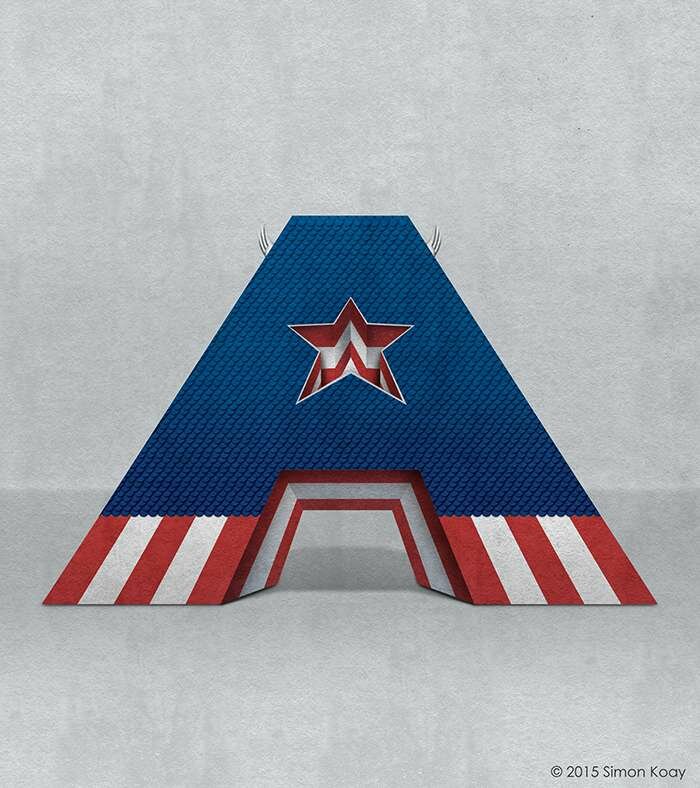
2. ตัวอักษร B ในสัญลักษณ์เป็น แบทแมน
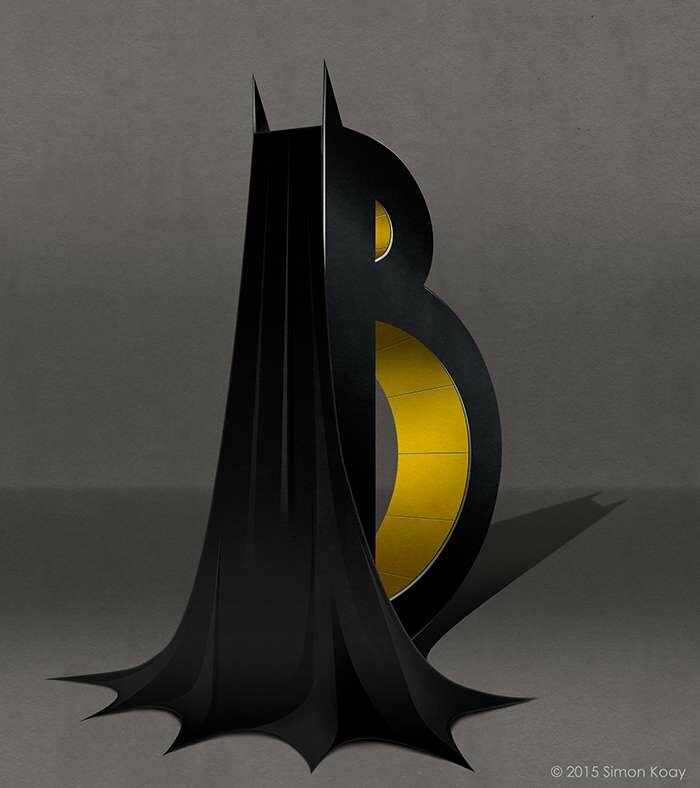
3. ตัวอักษร C ในสัญลักษณ์เป็น ไซคลอป
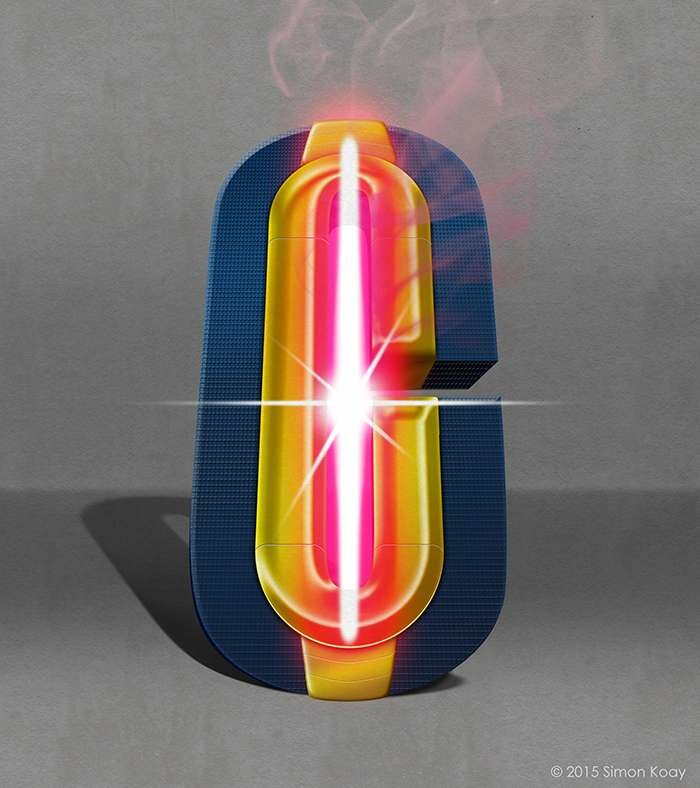
4. ตัวอักษร D ในสัญลักษณ์เป็น เดดพูล
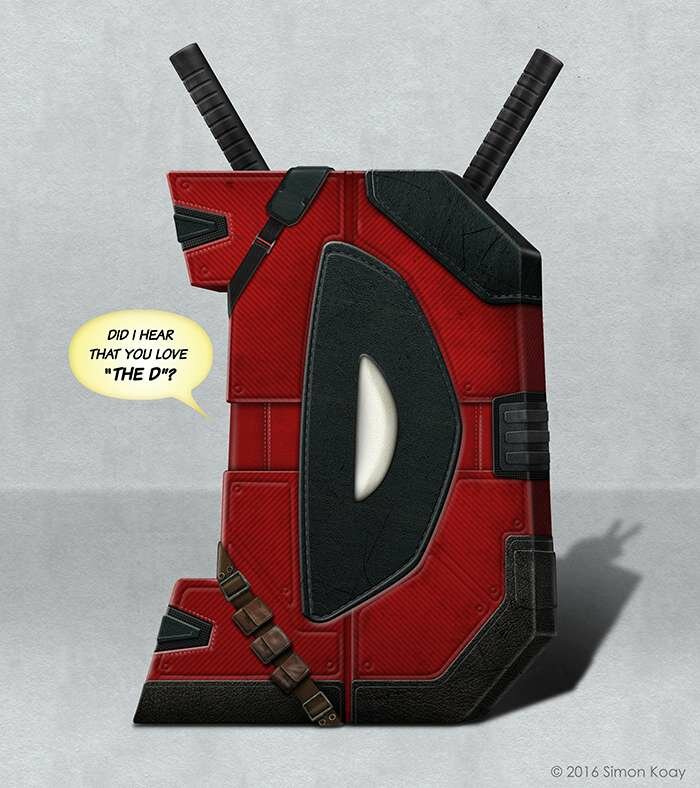
5. ตัวอักษร E ในสัญลักษณ์เป็น Elektra Black Angel
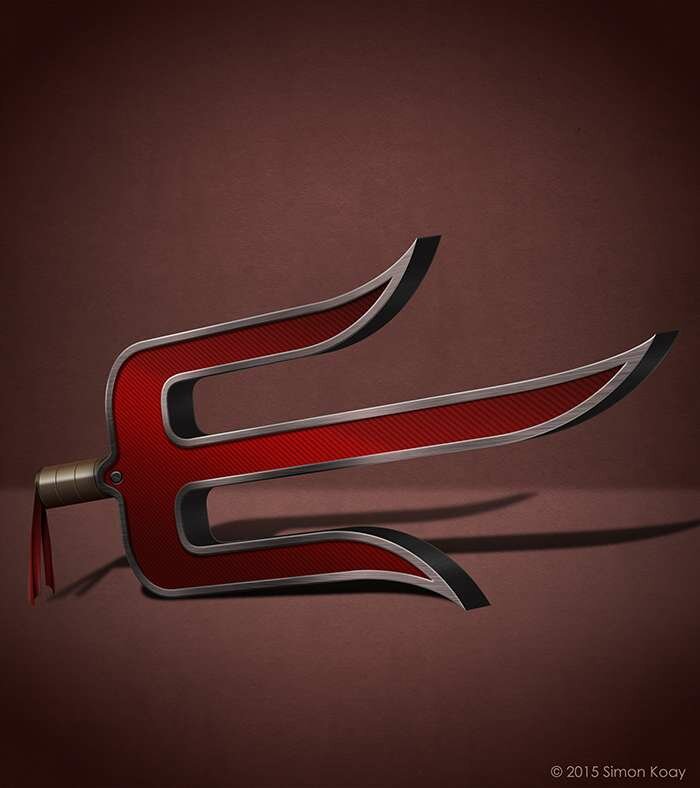
6. ตัวอักษร F ในสัญลักษณ์เป็น เดอะ แฟลช
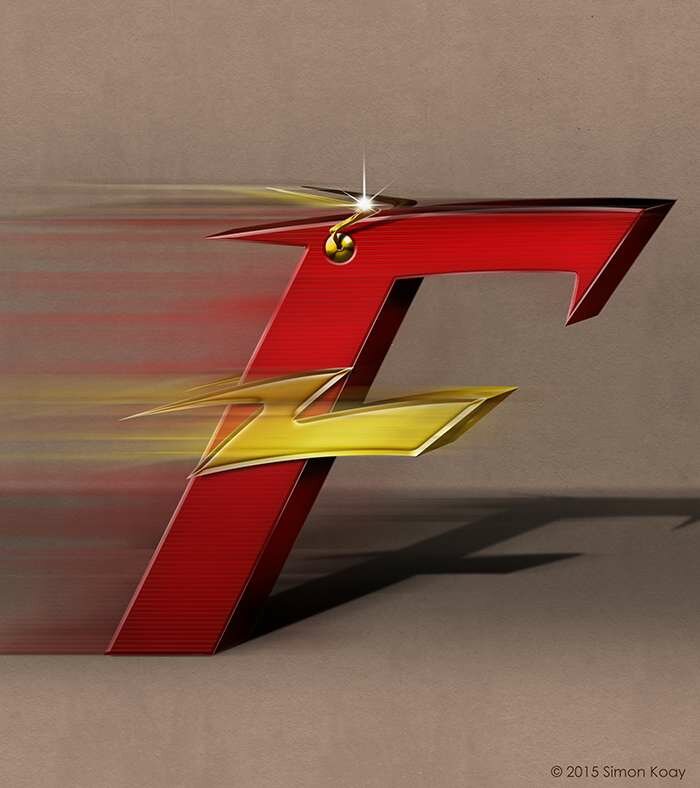
7. ตัวอักษร G ในสัญลักษณ์เป็น โกสไรเดอร์
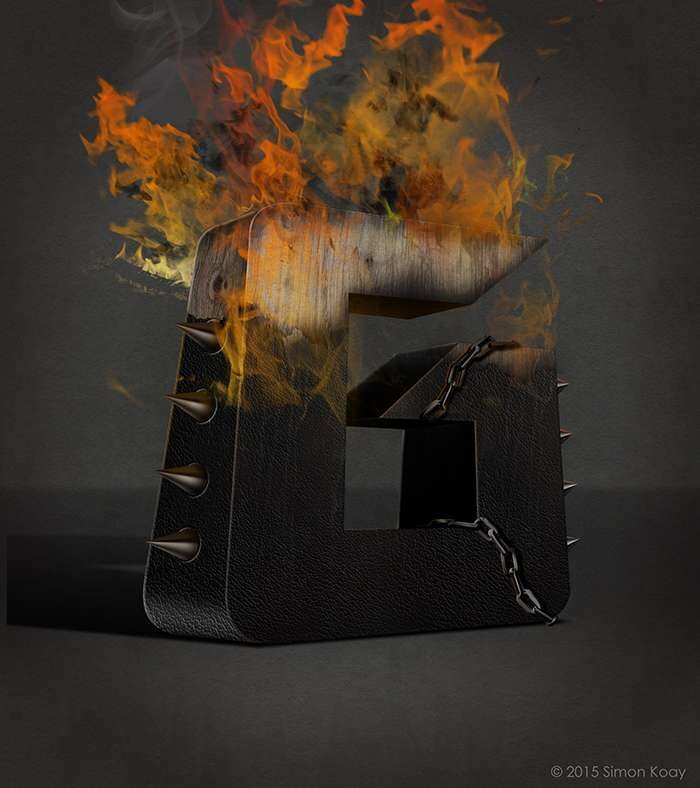
8. ตัวอักษร H ในสัญลักษณ์เป็น ฮัค
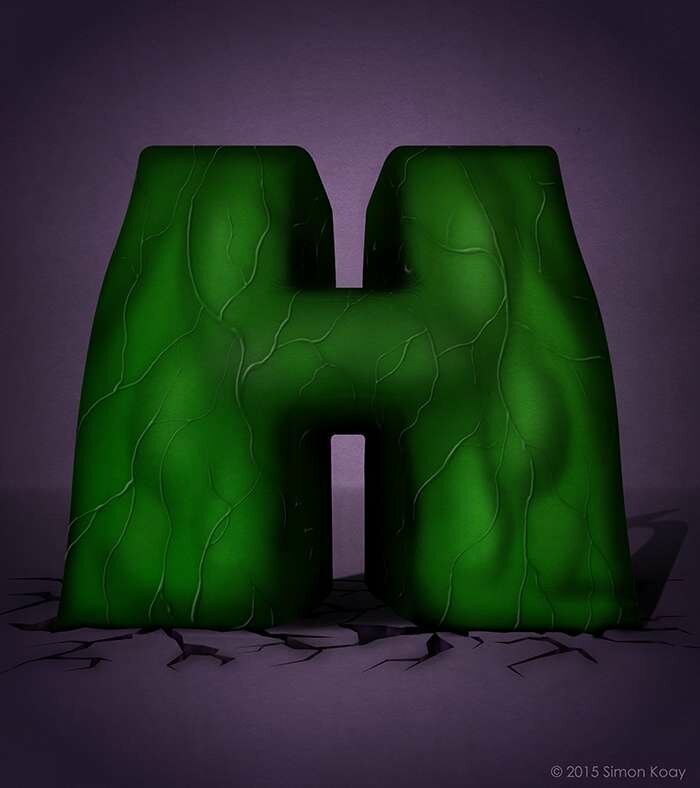
9. ตัวอักษร I ในสัญลักษณ์เป็น ไอรอนแมน
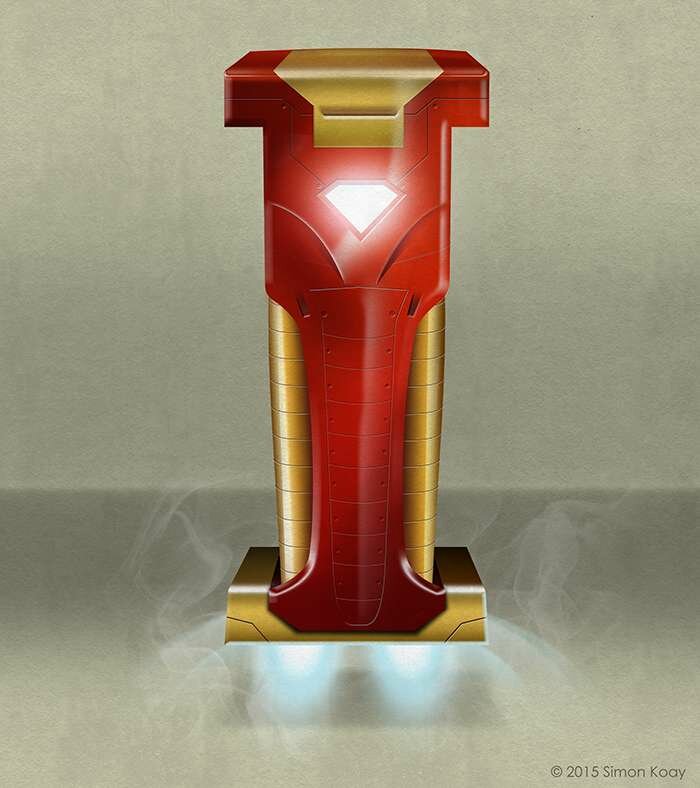
10. ตัวอักษร J ในสัญลักษณ์เป็น โจ๊กเกอร์
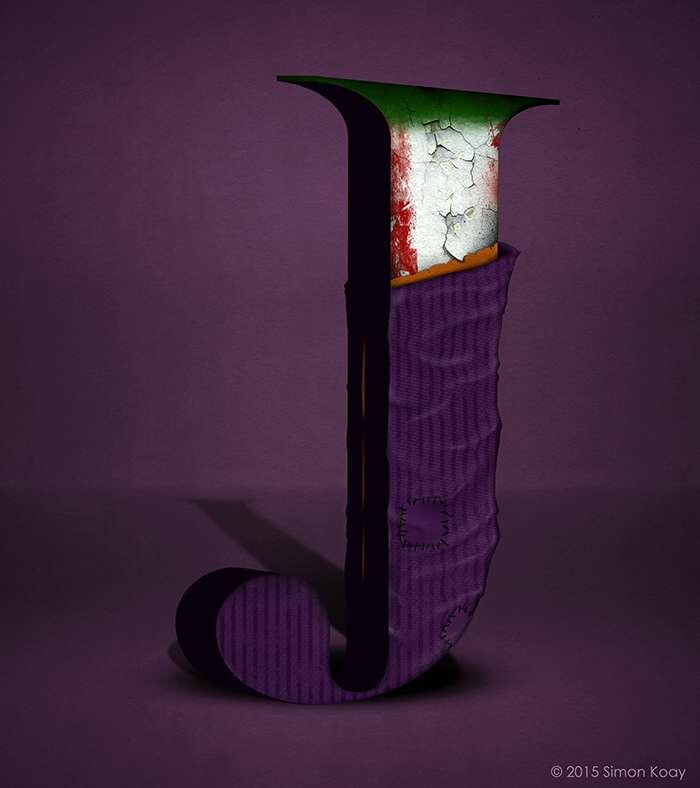
11. ตัวอักษร J ในสัญลักษณ์เป็น คิลเลอร์ คร็อค
12. ตัวอักษร L ในสัญลักษณ์เป็น โลกิ
13. ตัวอักษร M ในสัญลักษณ์เป็น มิสทีค (Mystique)
14. ตัวอักษร N ในสัญลักษณ์เป็น Nightcrawler
15. ตัวอักษร O ในสัญลักษณ์เป็น Omega Red
16. ตัวอักษร P ในสัญลักษณ์เป็น Poison Ivy
17. ตัวอักษร Q ในสัญลักษณ์เป็น Quicksilver
18. ตัวอักษร R ในสัญลักษณ์เป็น Riddler
19. ตัวอักษร S ในสัญลักษณ์เป็น Spider Man
20. ตัวอักษร T ในสัญลักษณ์เป็น Two-Face
21. ตัวอักษร U ในสัญลักษณ์เป็น Ultron
22. ตัวอักษร V ในสัญลักษณ์เป็น Venom
23. ตัวอักษร W ในสัญลักษณ์เป็น Wolverine
24. ตัวอักษร X ในสัญลักษณ์เป็น Professer
25. ตัวอักษร Y ในสัญลักษณ์เป็น Yellow Jacket
26. ตัวอักษร Z ในสัญลักษณ์เป็น Zatannaa
เป็นอย่างไรบ้างครับกับการออกแบบของตัวอักษรแบบใหม่ ตอนนี้คุณบอกเราได้หรือยังว่าชอบแบบไหนมากกว่ากัน